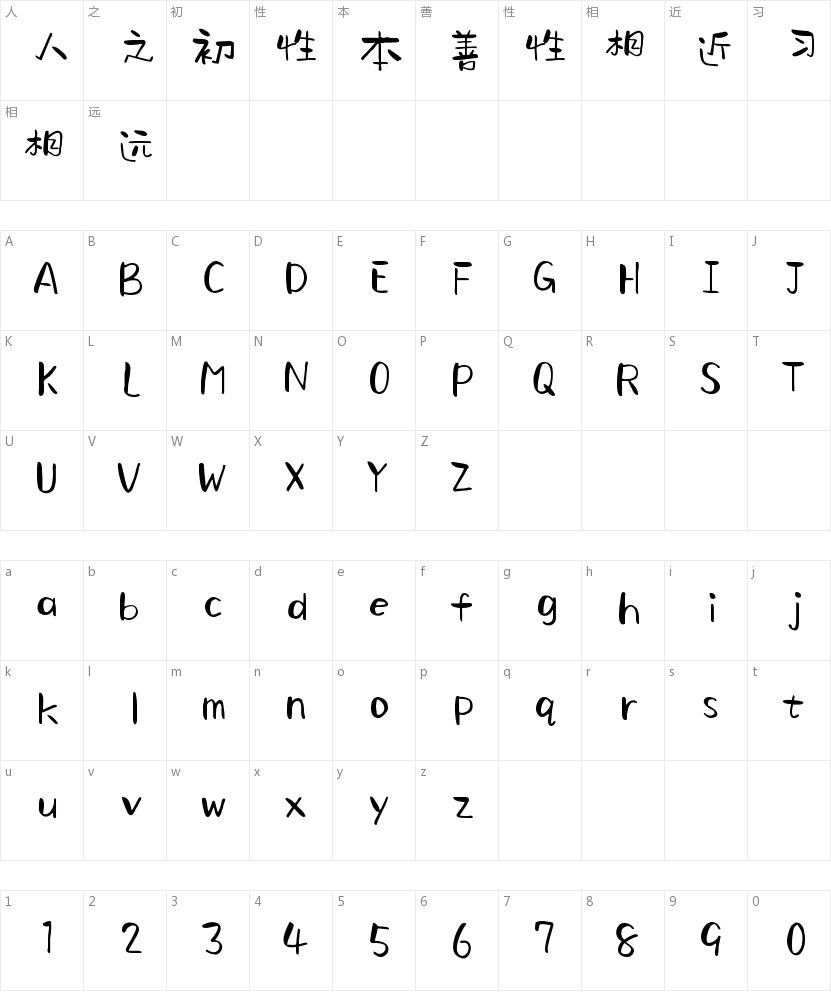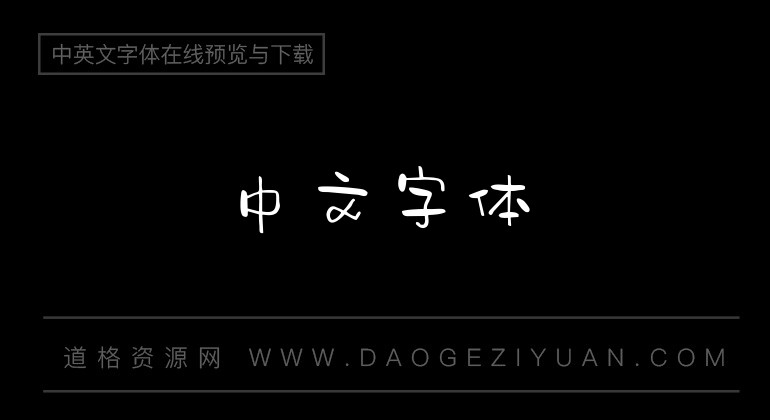
字心坊夏梦手书
心坊夏梦手书是一款由字体心坊出品的汉字书法字体,采用现代技术和传统书法的结合,融入了中国传统文化的元素,以创造出一种独特的书法风格。字体心坊夏梦手书拥有丰富的汉字字体,具有清新优雅的外观,让人们在书法创作中体会到中国传统文化的美感。此外,字体心坊夏梦手书还支持多种设备,可以在电脑、手机、平板电脑等设备上使用,让您在创作书法作品时能够更加方便快捷。
字心坊夏梦手书是一款非常不错的手写艺术字体,具有很好的视觉感,适合于文化类的宣传设计、商业类品牌的广告和产品包装设计以及个性化文字排版等较多场景。